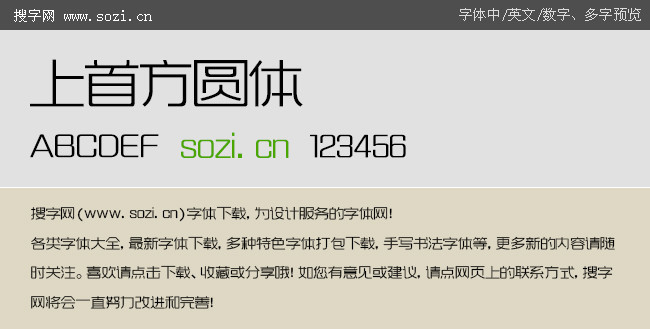
上首方圓體
搜字網(wǎng)給大家提供一款上首方圓體中文字體下載,上首方圓體,字體整體特征呈方圓形,筆畫(huà)粗細(xì)勻稱(chēng),字體下方轉(zhuǎn)角處作圓角處理,字體辨識(shí)度高,筆畫(huà)圓潤(rùn)流暢,看起來(lái)軟萌可愛(ài),帶幾分童趣,沒(méi)有攻擊性,給人舒適隨和的感覺(jué)。適用于兒童產(chǎn)品、娛樂(lè)性較強(qiáng)的地方。